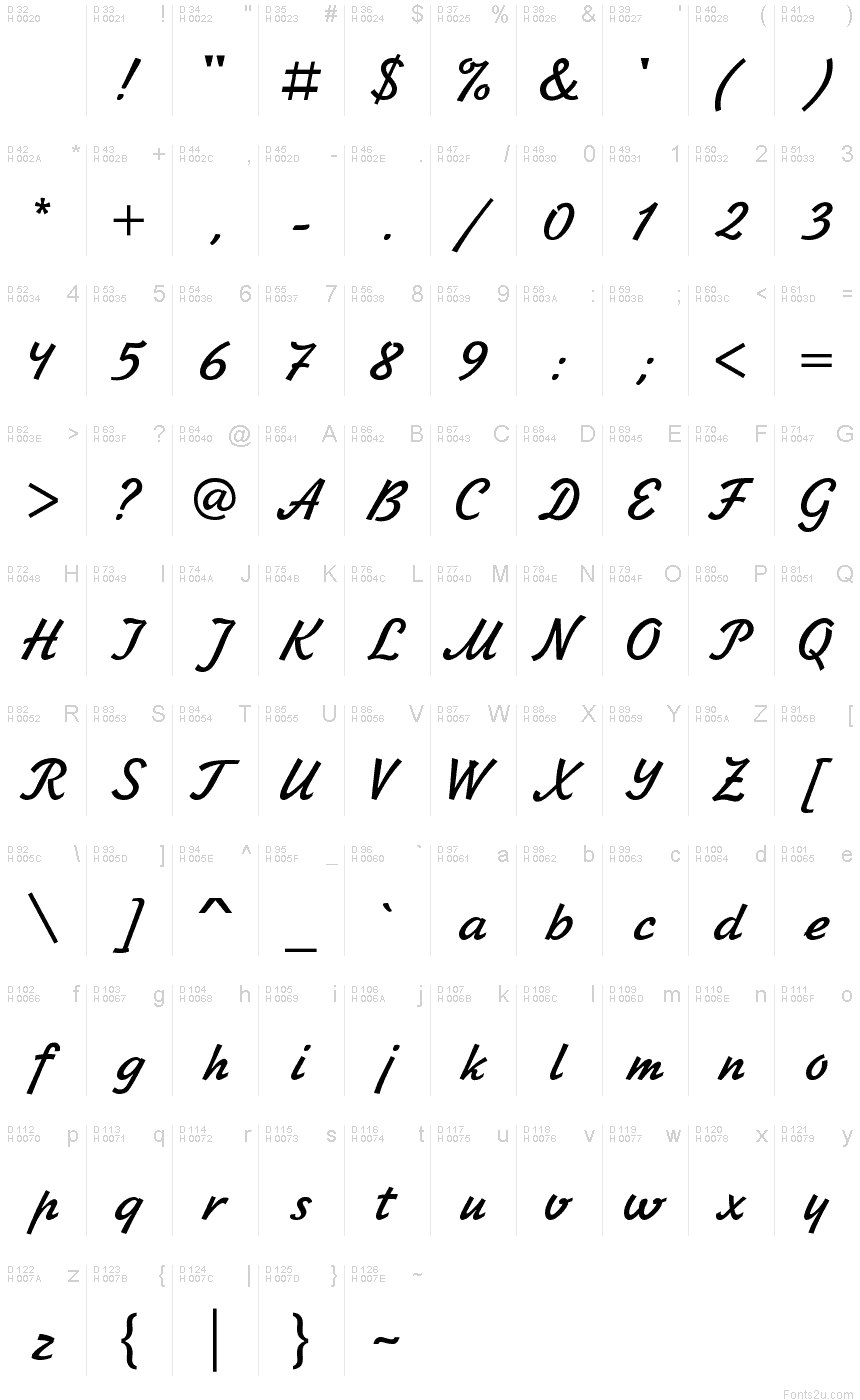
Jikharev è un font script calligrafico gratuito che scorre come inchiostro fresco su carta liscia. I tratti spessi e decisi si inclinano in avanti, mantenendo le lettere ben connesse, dando alle parole un ritmo rapido ed energico. Ha la ricercatezza della calligrafia senza risultare rigido: sembra più una firma dallo stile curato che una scrittura formale.
Con Jikharev, titoli e frasi brevi acquistano subito carattere, rendendolo perfetto per loghi, packaging, grafiche con citazioni, inviti, poster e titoli d'impatto per i social media. Questo font gratuito dà il meglio di sé in dimensioni grandi, dove le sue curve fluide e le forme aperte possono davvero respirare. Accostalo a un carattere sans serif pulito per il testo principale, così da mantenere il layout nitido e leggibile.
Jikharev